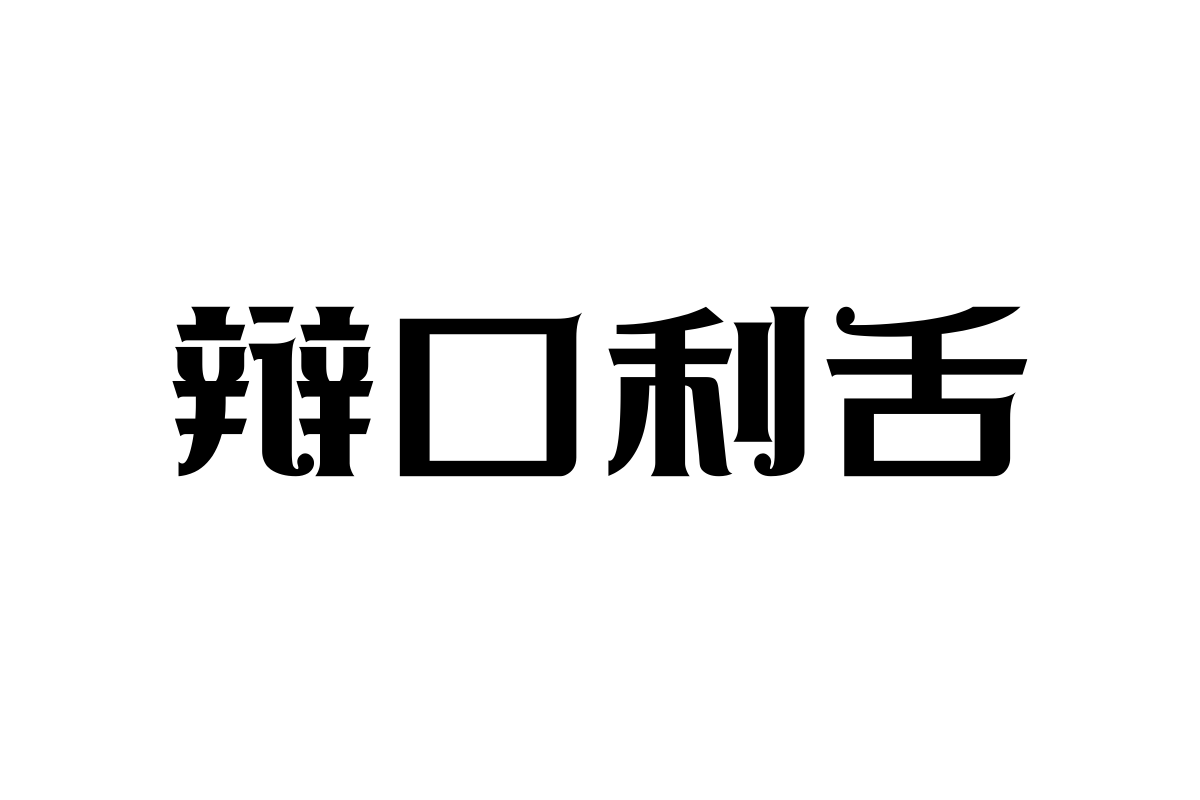
上首车车体字体是一种具有独特风格的中文字体,其特点是笔画流畅、字形饱满。这种字体在设计中常常被用于标题、广告、宣传等场合,以吸引观众的注意力。
上首车车体字体的特点如下:
1. 字形饱满:这种字体的字形饱满,给人一种稳重、大气的感觉,适合用于正式场合。
2. 笔画流畅:该字体的笔画流畅,易于阅读和识别,使得整体效果更加美观。
3. 风格独特:上首车车体字体具有独特的风格,与其他字体相比具有明显的区别,能够给人留下深刻的印象。
4. 适应性强:这种字体适用于各种场景,无论是文字还是图形设计,都能够很好地融入其中。
总的来说,上首车车体字体是一种非常实用的中文字体,适用于各种需要强调视觉效果的设计项目。